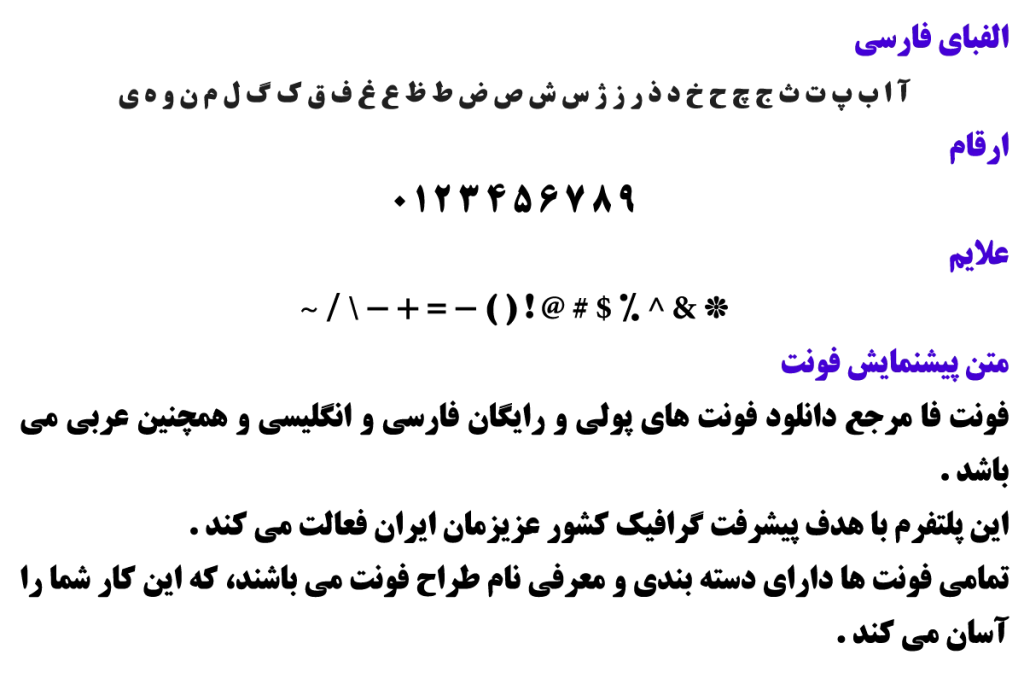
فونت فارسی تیتر – B Titr
پیشنمایش فونت تیتر
توضیحات و معرفی فونت تیتر
فونت فارسی تیتر ( B Titr ) از مجموعه فونت های آزاد می باشد، همچنان نوع فونت عنوان می باشد.
فونت شگفت انگیز و زیبای فوق توسط برنا رایانه طراحی و ساخته شده است.
تیتر فونتی است که مشابه فونت های فونت تیتر پلاس است، اما با کمی تغییر…
همچنان فونت B Titr در یک وزن پر رنگ است.
در لیست زیر می توانید وزن این فونت شگفت انگیز و زیبا را ببینید.
- B Titr Bold
شعر میهنی زیر با این تایپ فیس طراحی شده و نمایانگر زیبایی آن است.